Качество кириллицы в логотипе: что проверить до утверждения
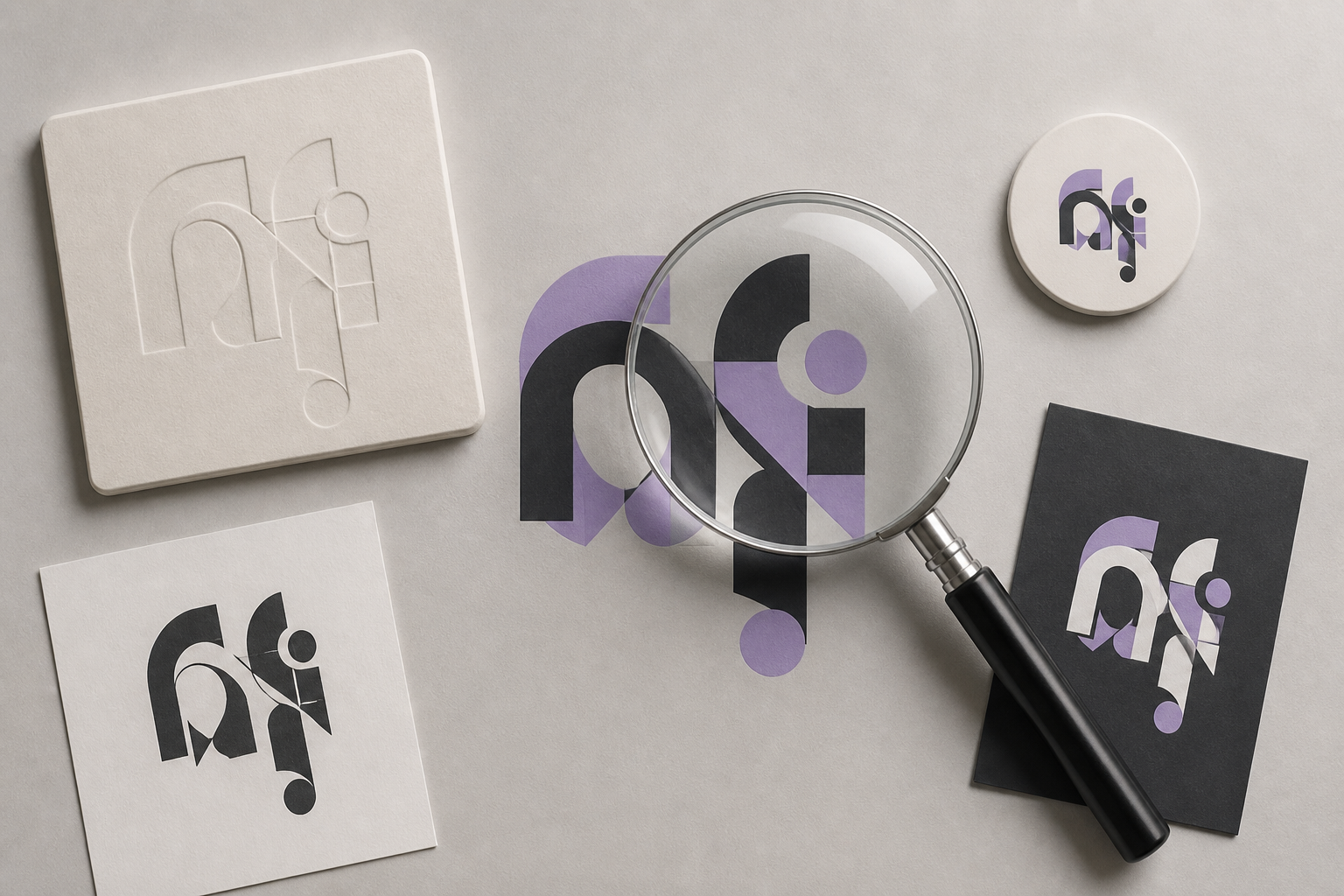
Качество кириллицы в логотипе определяется не только красотой отдельных букв, но и тем, насколько цельно, читаемо и стабильно слово выглядит в разных размерах и носителях. До утверждения макета нужно проверить формы специфических кириллических знаков, интервалы, кодировку, контраст, малые размеры, чёрно-белую версию и соответствие характеру бренда.
Почему кириллический логотип требует отдельной проверки
Кириллица не является простой заменой латиницы. Даже если гарнитура хорошо выглядит в английском названии, русское слово может потребовать другой настройки пропорций, высоты знаков и расстояний между ними. На восприятие влияют буквы Д, Л, Ц, Щ, Ж, Ф, У, Ч, Ь, Ъ, Ы, Э, Ю и Я: именно они чаще всего раскрывают слабые места шрифта и заставляют логотип выглядеть случайным набором символов.
Проверяйте не только рисунок, но и цифровую корректность
В макете должны использоваться настоящие кириллические символы, а не визуально похожие латинские знаки. Латинские А, Е, К, М, О, Т, Х и кириллические А, Е, К, М, О, Т, Х могут выглядеть одинаково или почти одинаково, но имеют разные кодовые позиции. Ошибка становится заметной при копировании названия, поиске, адаптации логотипа, подготовке файлов и автоматической обработке текста.
Какие буквы и сочетания проверить в первую очередь
Начните с полного названия бренда, а затем отдельно протестируйте самые сложные символы. В хорошем кириллическом логотипе каждая буква сохраняет узнаваемую национальную форму, но при этом поддерживает общий пластический ритм. Особенно важно не копировать латинскую конструкцию механически: у кириллицы есть собственная система пропорций, характерные верхние и нижние элементы, а также свои способы уравновешивать слово.
- Сравните Д и Л: проверьте основание, наклонные элементы и визуальный вес в соседстве с округлыми буквами.
- Проверьте Ц и Щ: убедитесь, что нижние выносные элементы не сливаются и не ломают общий ритм строки.
- Рассмотрите Ж, К и Х: оцените пересечения диагоналей, плотность центра и равномерность чёрного.
- Проверьте Ф и О: сравните внутренние просветы и убедитесь, что центральная часть не выглядит слишком тяжёлой.
- Оцените У, Ч и Р: эти знаки могут создавать неожиданные провалы или скопления тёмных участков.
- Отдельно проверьте Ь, Ъ, Ы и Э: малые детали должны оставаться различимыми, особенно в компактном варианте.
- Посмотрите на Ю и Я: крайние буквы слова не должны визуально перевешивать соседние знаки.
- Проверьте повторяющиеся буквы и пары вроде ЛЛ, ТТ, СТ, РА, ОЛ и ИИ: именно в них часто проявляется неудачный кернинг.
Форма букв, пропорции и характер бренда
Логотипный шрифт может быть строгим, технологичным, дружелюбным, премиальным или рукописным, но его характер должен считываться через всю кириллическую систему. Нельзя оценивать одну эффектную букву отдельно от слова: необычная форма Д или Ж оправдана только тогда, когда остальные знаки поддерживают тот же уровень выразительности. Иначе логотип превращается в набор декоративных приёмов.
Проверьте пропорции и внутренние просветы
Сравните ширину букв, высоту строчных и прописных знаков, размер апертур и внутренних пространств. Если просвет в О заметно шире просвета в В, а Р или Ф выглядят почти заполненными, слово потеряет равномерность. Для логотипа важна не математическая одинаковость, а оптический баланс: одинаковая ширина элементов на сетке не гарантирует одинаковый визуальный вес.
Оцените толщину штрихов и места соединений
В жирном начертании внутренние пространства кириллических букв быстро уменьшаются, а тонкие соединения могут исчезать при уменьшении. Посмотрите на пересечения диагоналей в Ж, К и Х, на центральную часть Ф и на нижние элементы Ц и Щ. Если штрихи сталкиваются слишком плотно, буквы начинают выглядеть грязными; если контраст чрезмерен, слово теряет устойчивость в печати и на экране.
Интервалы, кернинг и оптическое выравнивание
Автоматический кернинг редко даёт готовый логотип. Кириллическое название нужно просматривать как цельную форму, а не как сумму расстояний между парами. В слове с округлыми буквами визуальные промежутки обычно воспринимаются иначе, чем в слове с вертикалями и диагоналями. Поэтому расстояния между ОЛ, ЛО, ТА или АЯ могут требовать ручной настройки даже при корректных шрифтовых метриках.
Практический тест прост: уменьшите слово до рабочего размера, прищурьтесь или отойдите от экрана и посмотрите, не распадается ли строка на отдельные пятна. Затем переведите макет в контуры и сравните его с версией, набранной текстом. Если после ручной коррекции логотип стал собраннее, но буквы сохранили читаемость, настройка оправдана. Не следует выравнивать интервалы линейкой без проверки общего силуэта.
Проверка читаемости в разных размерах и средах
Логотип существует не только на презентационном слайде. Он может оказаться на аватаре, упаковке, вывеске, визитке, мобильном экране, вышивке или небольшом рекламном носителе. Поэтому проверяйте не один красивый мастер-макет, а диапазон сценариев. Основная версия должна сохранять узнаваемость, а для сложных случаев может понадобиться компактная версия с упрощёнными деталями и отдельной настройкой интервалов.
Качественный кириллический логотип — это не просто красивый шрифт, а согласованная система форм, пропорций, интервалов и сценариев использования. До утверждения проверьте специфические буквы, цифровую корректность, малые размеры, инверсию, печать и читаемость без подсказок. Если готовой гарнитуры недостаточно, создайте или адаптируйте шрифт под задачу на fontgenerator.ru.